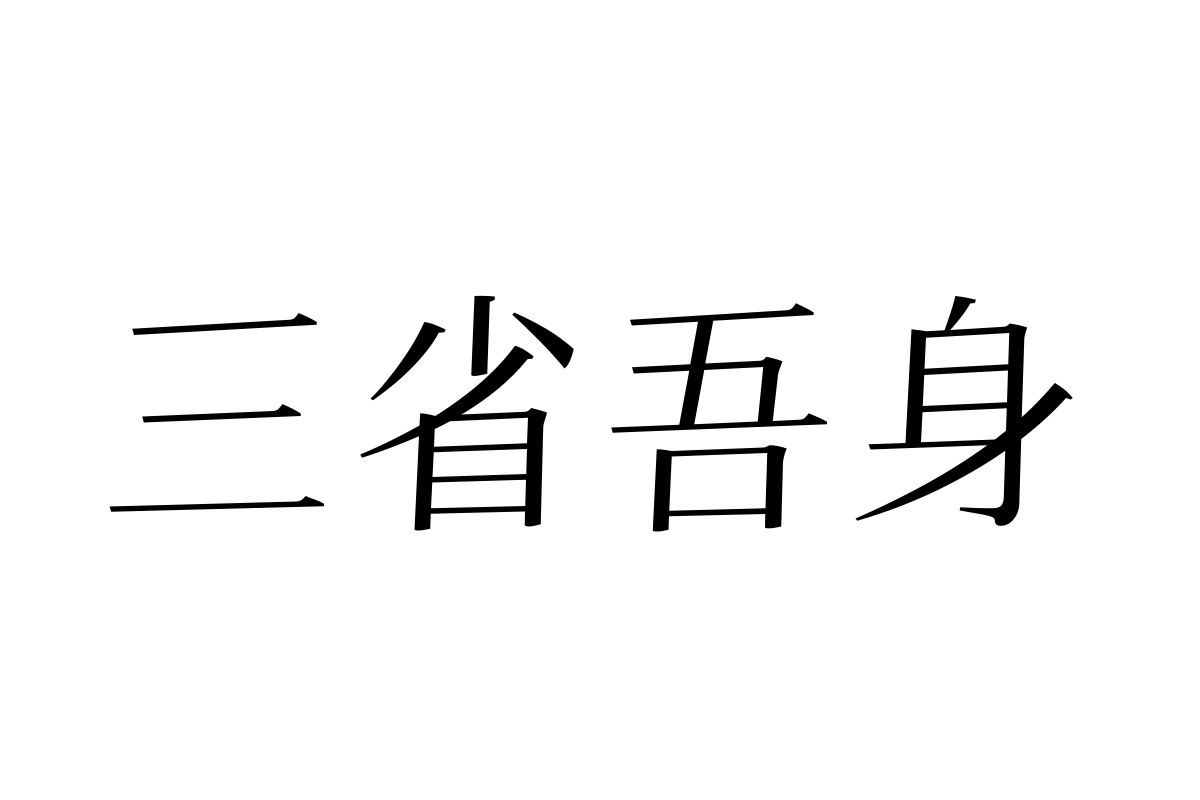
汉仪瑞意宋I 45W是一款具有独特风格的中文字体,适用于需要强调品牌特色和文化内涵的场合。这款字体采用了现代设计手法,将传统的宋体风格与现代元素相结合,创造出独特的视觉感受。
字体特点:
1. 字形规整,线条流畅,给人以清晰、易读的感觉。
2. 笔画粗细变化丰富,既有粗犷的线条,又有细腻的勾线,适合各种设计风格的需求。
3. 字体结构紧凑,易于排版和印刷,适合用于书籍、杂志、报纸等出版物。
适用场景:
1. 品牌宣传:适用于需要突出品牌形象和文化内涵的各类宣传材料,如广告、海报、包装等。
2. 网站设计:适用于各类网站标题、正文、广告等文字内容的设计。
3. 印刷制品:适用于书籍、杂志、报纸等印刷品的文字排版。